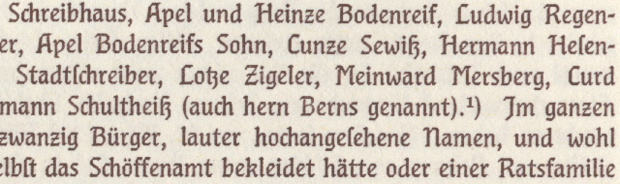
Was für eine Schrift ist das (aus Buch um 1913) ?
aus reinem Interesse würde ich gerne mehr über diese Schrift erfahren, die in dem Buch "Geschichte der Residenzstadt Cassel" benutzt wird. Das Buch stammt aus 1913 und ist im Verlag Pillardy & Augustin, Cassel, erschienen.
Die Schrift ist etwas merkwürdig (zumindest für einen Typografielaien wie mich), da sie eine Mischung aus Antiqua und Fraktur zu sein scheint. Zumindest gelten wohl die Regeln für das "Mitten-s" und das "End-s", das "sz" und das "tz" sind auch Fraktur (oder haben Elemente davon). Das einzelne "z" ist wie bei einer Antiqua, aber mit Mittelstrich.
Die Großbuchstaben sind nicht aus einer Fraktur und haben keine Elefantenrüssel o.ä.
Irgendein Hinweis ?
Von diesen Mischschriften gibt es mehrere, bekannter sind die Eckmann-Schrift, die Behrens-Schrift, die Hohenzollern und die Augsburger. Von denen ist es keine. Ich glaube allerdings, daß ich auch Deine schonmal gesehen habe, kann mich aber leider nicht an den Namen oä. erinnern.
Ich habe auch so ein Buch (um 1920) mit einer solchen als Brotschrift, und verblüffenderweise liest sie sich richtig gut. Natürlich ist sie nirgends benannt.